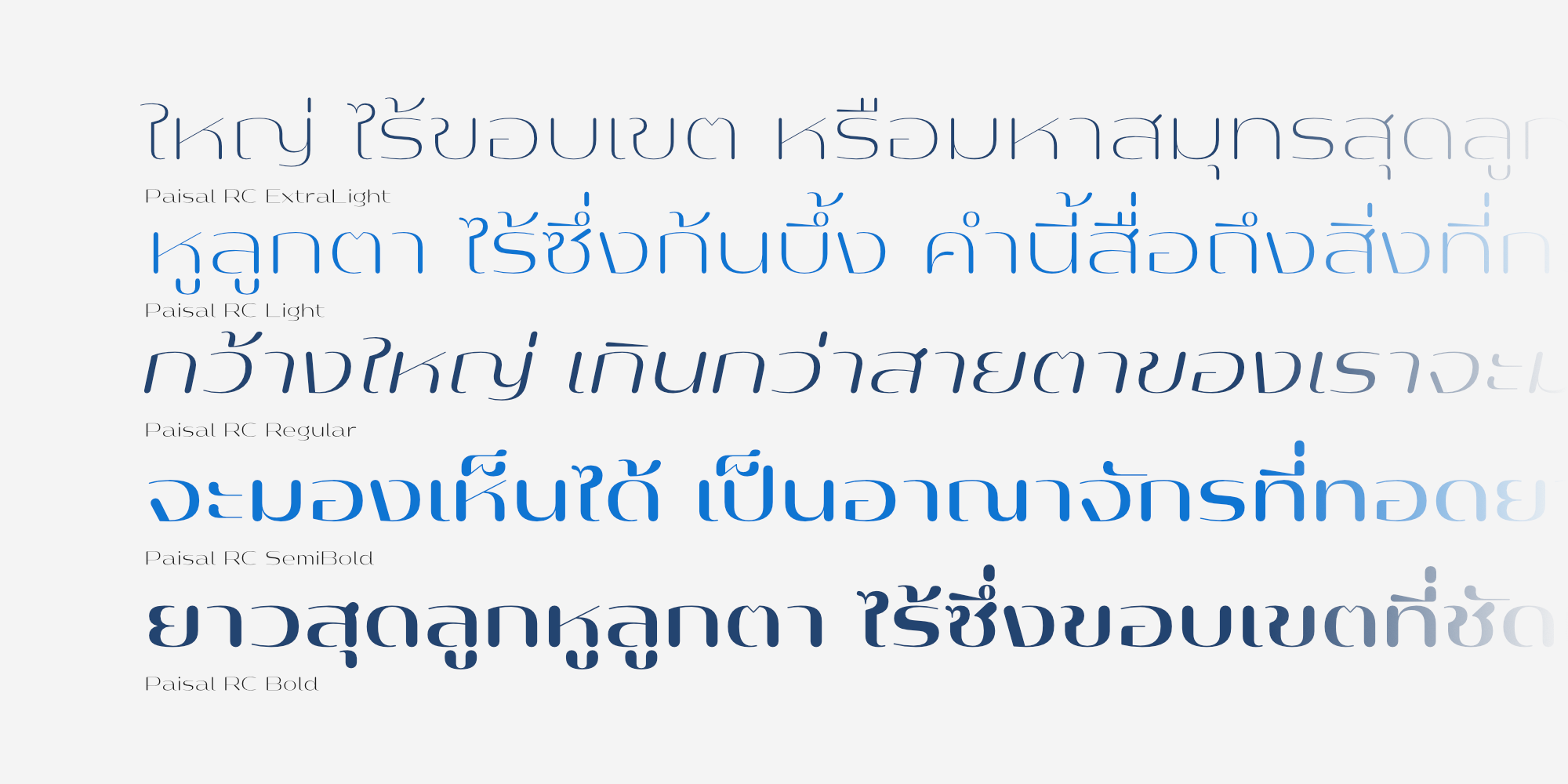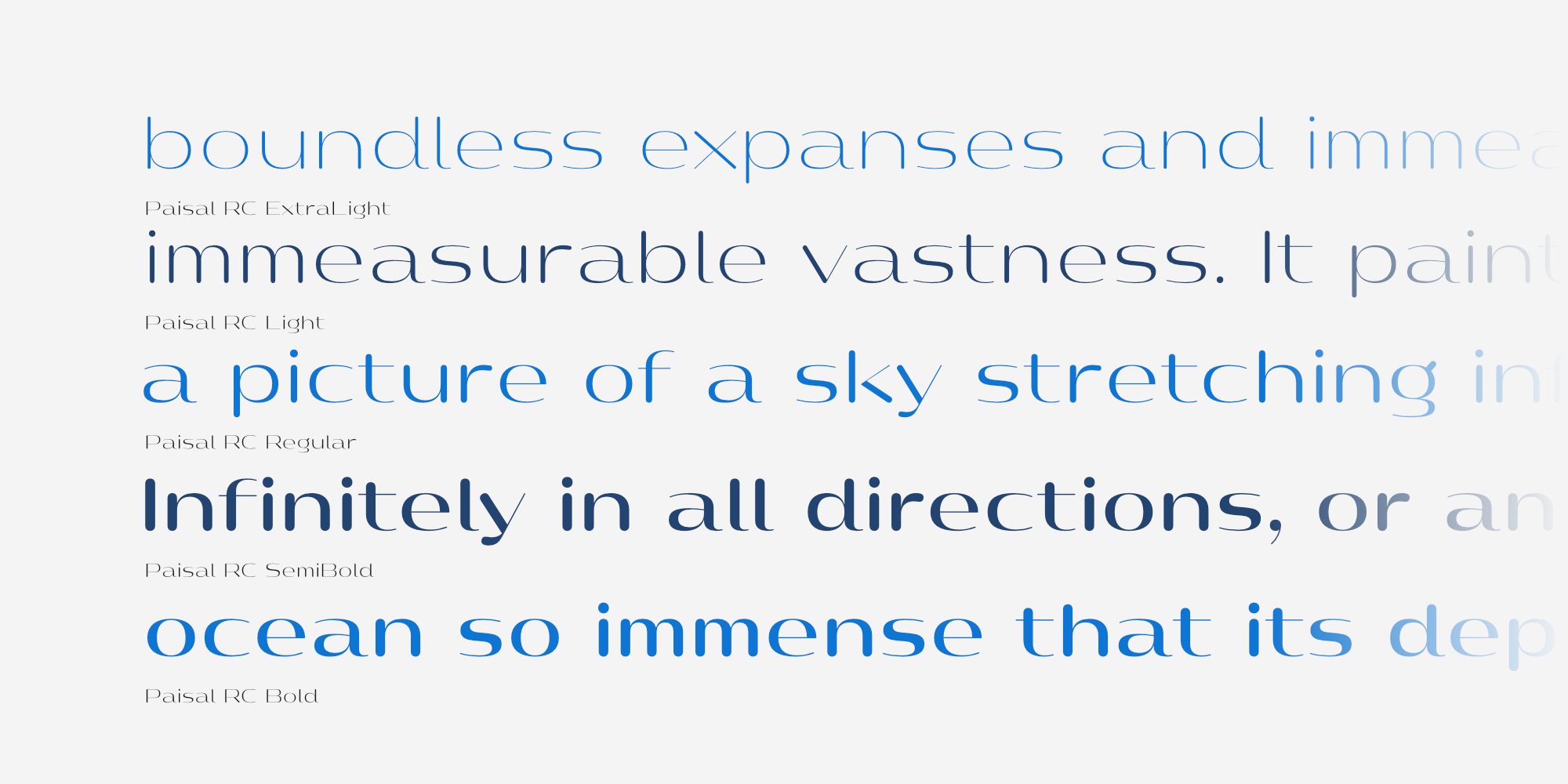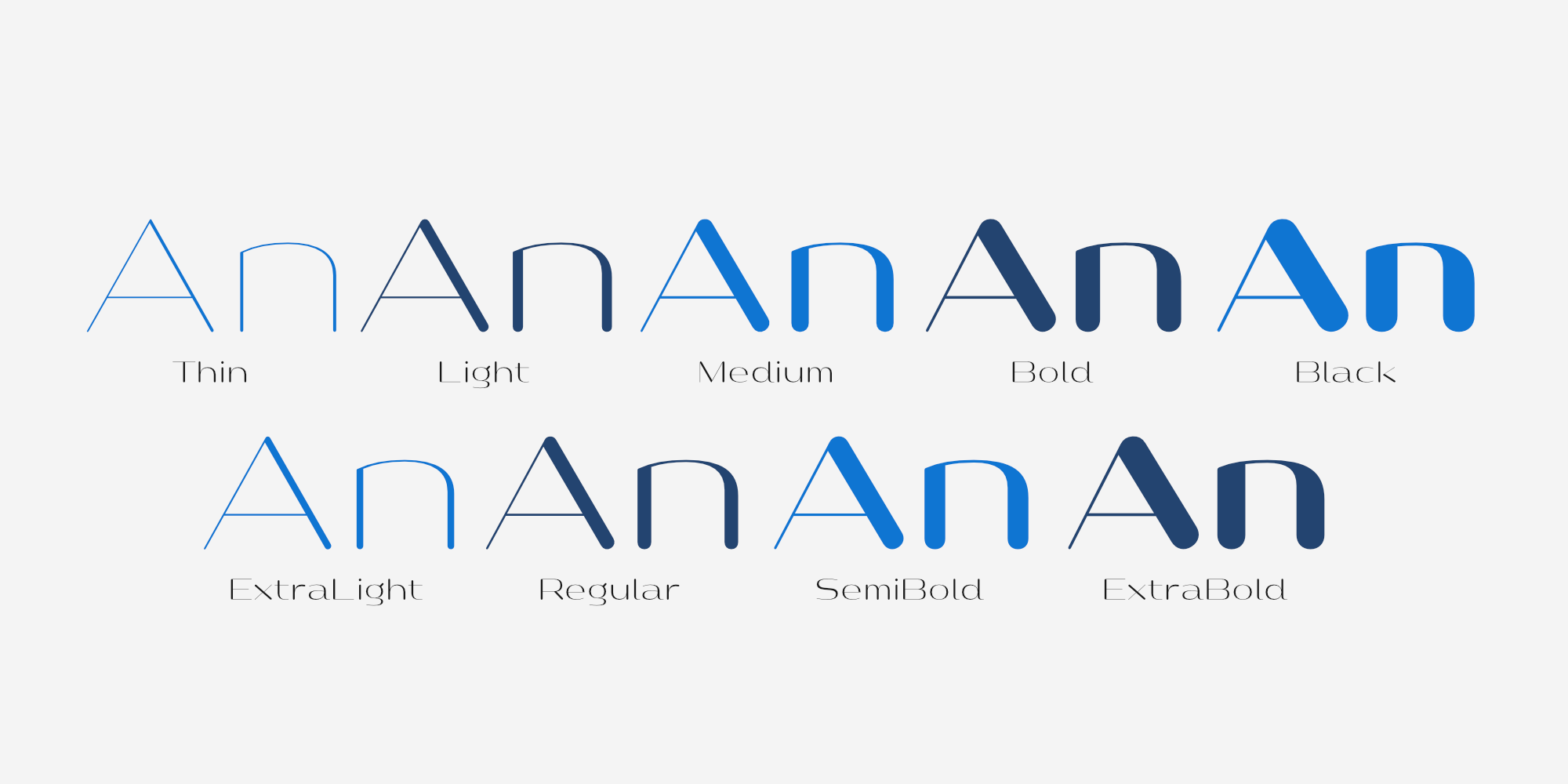
ไพศาลอาร์ซี | Paisal RC
ชื่อฟอนต์ : ไพศาลอาร์ซี | Paisal RC
แบบอักษร Paisal RC (Rounded-Contrast) เป็นแบบอักษรที่ได้รับการพัฒนาต่อยอดจากแบบอักษร Paisal Rounded และ Paisal Contrast เป็นการผสมสองแบบอักษรเข้าด้วยกัน ส่งผลให้โครงสร้างแบบอักษรนี้มีลักษณะกลมมนและเปรียบต่าง แบบอักษรนี้ประกอบด้วย 18 รูปแบบ ครอบคลุมตั้งแต่น้ำหนักเส้นบางที่สุดไปจนถึงหนาที่สุด โดยรองรับทั้งชุดอักษรลาติน 1 และอักษรไทย แบบอักษร Paisal RC เหมาะสำหรับการใช้งานในสิ่งพิมพ์ต่าง ๆ ทั้งในรูปแบบออนไลน์และออฟไลน์ โดยเฉพาะการใช้งานในส่วนพาดหัว เช่น นิตยสารความสวยความงาม คลินิกงาม สปา และอื่น ๆ ในหมวดเดียวกัน
Creator : อานุภาพ ใจชำนาญ (Anupap Jaichumnan)